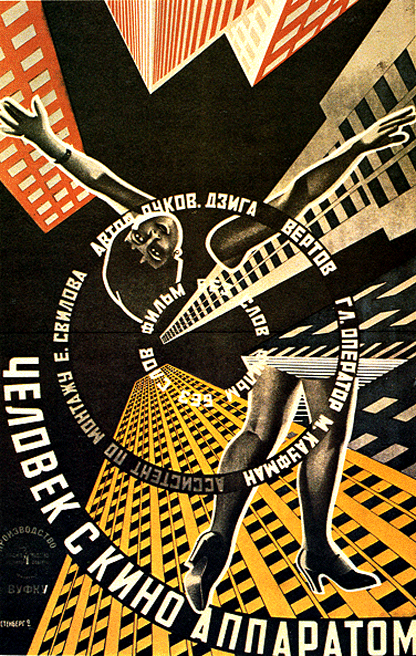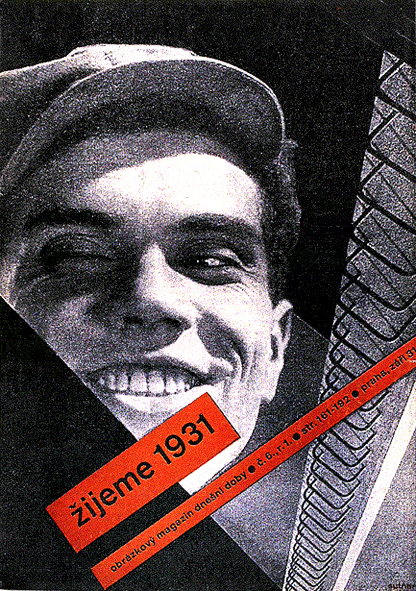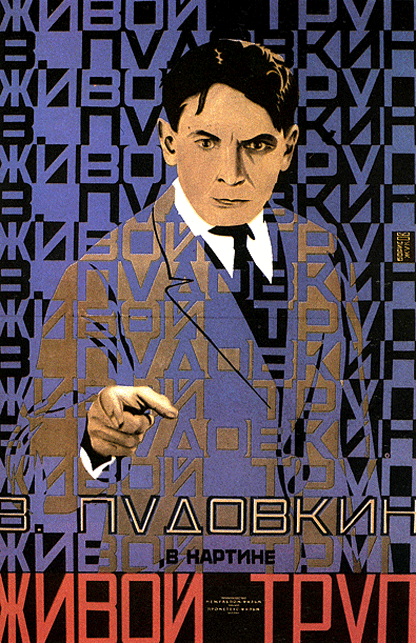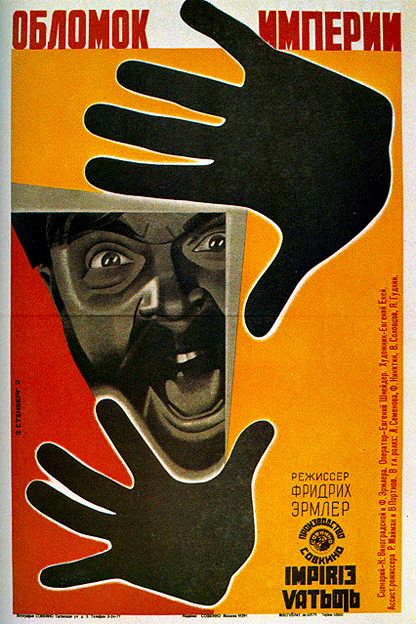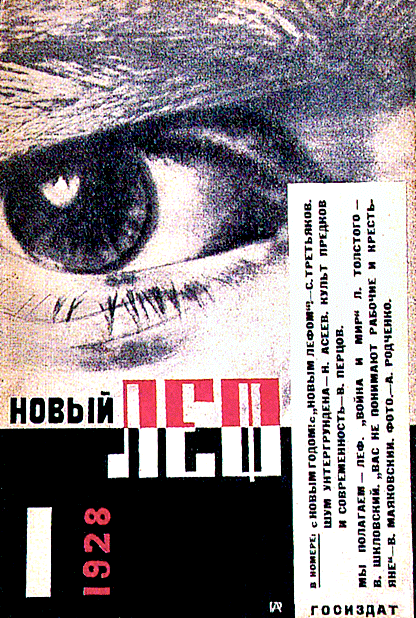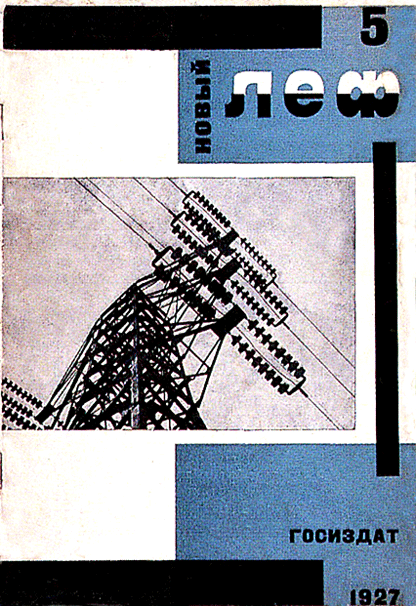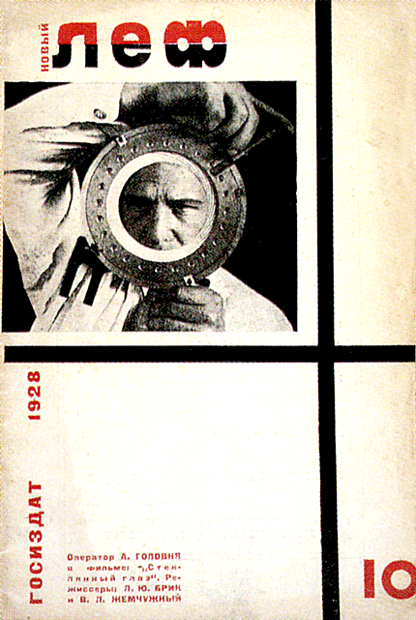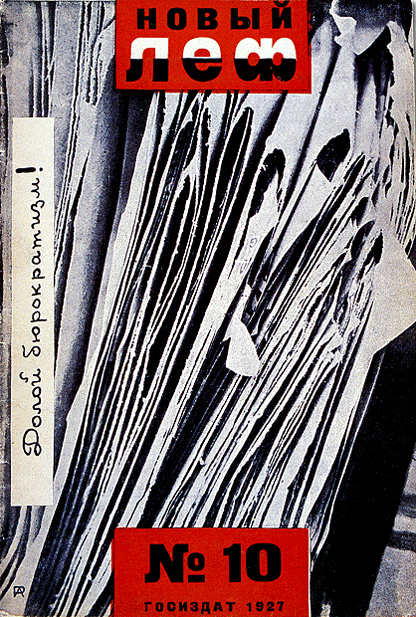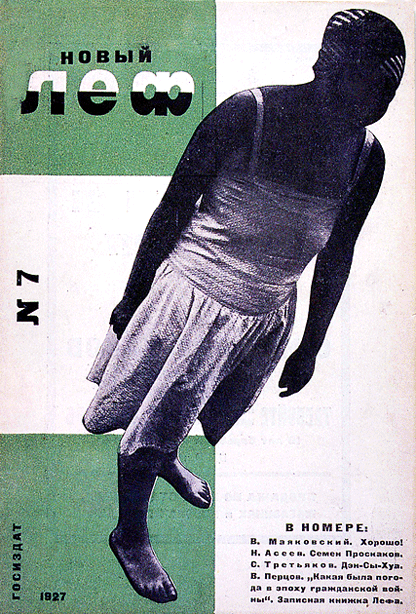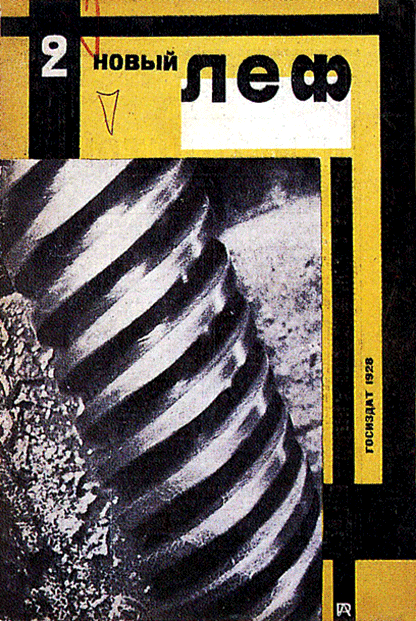
Cover for the periodical Poligraphic Production designed either by Stepanova or Rodchenko 1946. It’s sometimes difficult to tell who did what on their work.
Bastard title from the photo album The Red Army, designed by Rodchenko and Stepanova 1938. Russian Constructivism.
Older Lef (Left Front for the Arts) cover designed by Rodchenko, Russian Constructivist 1923
Novyi Lef cover designed by Rodchenko using his own photography 1927. Russian Constructivism.
Double-page spread for The USSR Under Construction, an issue with an article on Maiakovsky designed by Rodchenko and Stepanova 1940.
Russian Constructivist film poster utilizing photomontage, designed by Georgi and Vladimar Stenberg 1929
Novyi Lef cover designed by Rodchenko using his own photography 1928. Russian Constructivism.
Redesigned Novyi Lef cover by Rodchenko, Russian Constructivist 1928
Photomantage cover designed by El Lissitzky for the publication Artists’ Brigade1931. Russian Constructivism.
Cover for “The Results of the First Five-Year Plan” desgined by Stepanova and or Rodchenko, Russian Constructivist 1933. The photo-montage of Constructivism
I think a Paul Schuitema design but I’m not sure.
Cover for “Children and the Cinema” designed I think by Varvara Stepanova, (Rodchenko too?) Russian Constructivist 1928. The photomontage of Constructivism
Redesigned Novyi Lef cover by Rodchenko, Russian Constructivist 1928
Inside double page spread from “The Results of the First Five-Year Plan” designed by Varvara Stepanova, Russian Constructivist 1932. The photomontage of Constructivism.
Cover for USSR Under Construction designed by Rodchenko 1940
Novyi Lef cover designed by Rodchenko using his own photography 1928. Russian Constructivism
Redisigned Novyi Lef cover by Rodchenko, Russian Constructivist 1927. Photography, the mechanical art for the mechanical age. The vertical panel reads Down with Bureaucracy!
Novyi Lef cover designed by Alexandr Rodchenko, Russian Constructivist 1928